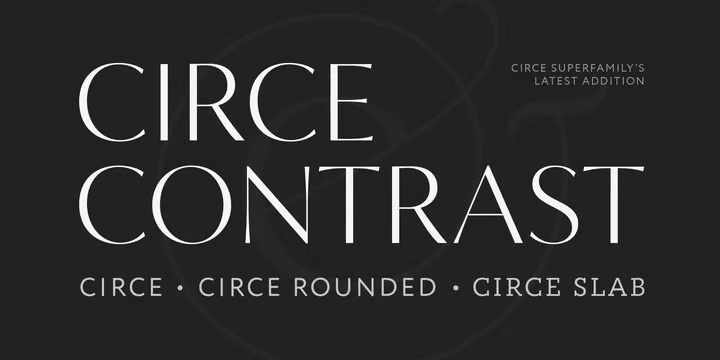
Circe Contrast
優雅なフレアセリフディスプレイ。化粧品のロゴによくありそうなコントラストの付いたサンセリフで、ストロークの端がやや広がってフレアセリフタイプとなっている。変わったリガチャーやオルタネートはなく、最近としては大変素直なグリフ構成である。代わりと言ってはなんだがコントラストがやや弱まった小見出し用の Subhead、さらに弱まった本文用の Text があり、それぞれに9ウェイトある。が、イタリックがないのであんまり本格的な長文には向かない。元は普通のジオメトリックサンセリフの Circe で、端が丸くなった Circe Rounded、大きなセリフが付いた Circe Slab の3種があったが、この度このファミリーが追加になった。名前のキルケーはギリシャ神話に登場する魔女のこと。ただいま50%オフセール中。